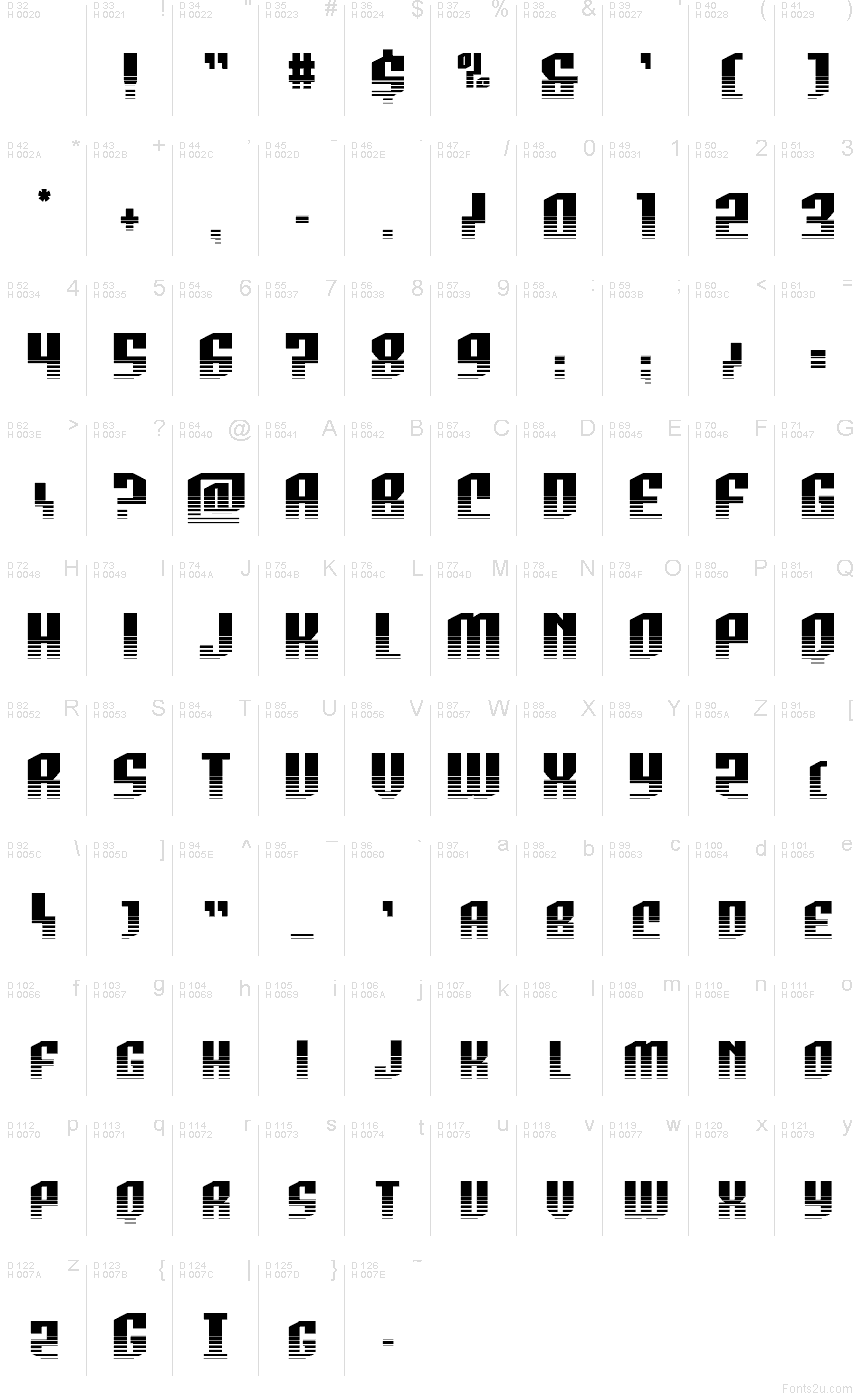
Viper Command Halftone autorstwa Daniela Zadorozny’ego z Iconian Fonts to darmowy font w stylu techno, którego tekstura przypomina wydruk skanera — solidne bloki poprzecinane wyraźnymi, rastrowymi paskami. Krępe, kwadratowe kształty i ścisły, mechaniczny rytm nadają mu charakteru zakodowanej instrukcji misji. Czyta się go pewnie i z kontrolą, niczym ostrzeżenia na grodziach statku kosmicznego.
Viper Command Halftone świetnie sprawdza się na plakatach sci-fi, w brandingu drużyn e-sportowych, nagłówkach interfejsów gier, cyberpunkowych ulotkach, promocjach wydarzeń technologicznych, okładkach albumów czy miniaturach na YouTube, gdzie potrzebujesz natychmiastowego efektu. Ustaw go w większym rozmiarze, aby detal z paskami mógł wybrzmieć, a w tekście głównym połącz go z czystym, geometrycznym bezszeryfem, dzięki czemu nagłówek pozostanie w centrum uwagi. Ten darmowy font wprowadza natychmiastową energię „konsoli dowodzenia” bez zbędnego chaosu.